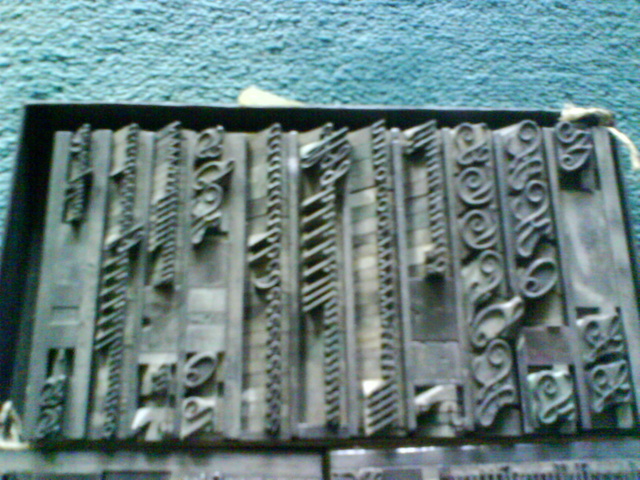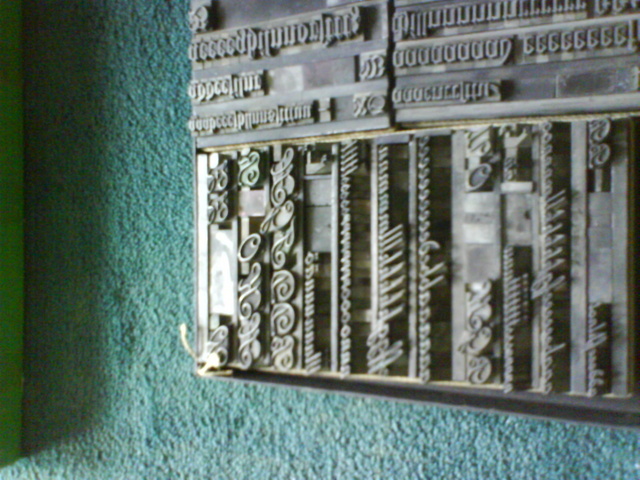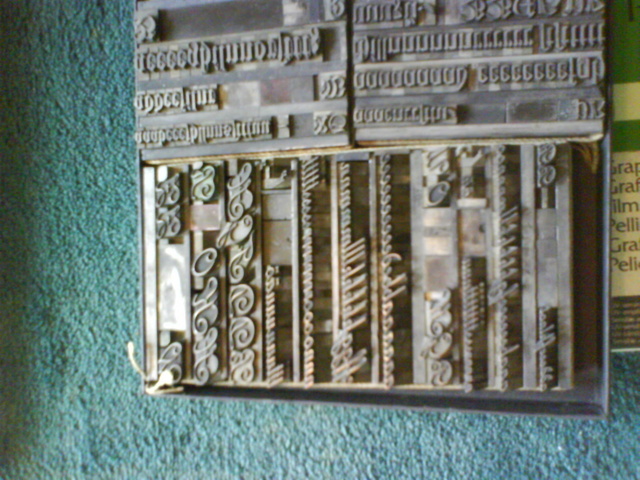
Ich habe bisher alle meine Schriftbücher durchsucht, habe allerdings keinen Treffer erzielt.
Nun hoffe ich hier auf Erfolg. Ich habe mal ein (schlechtes) Bildchen beigefügt.
Etwas zur Vorgeschichte. Ich habe einige Schriftfragmente "gerettet". Alles andere ging oder geht (demnächst) in die Schmelze. Es gibt zu dieser Schrift leider auch keine Schriftmusterbücher mehr. Was mich allerdings wundert, weil ich alle Schriftmusterbücher der betreffenden Firmen habe.
Anbei zwei weitere schlechte Bilder. Achja, die Kirnberg ist es nicht. Entstehungszeit etwa Jahrhundertwende...
Wenn mich meine schwachen Augen nicht sehr täuschen,
handelt es sich bei der Schreibschrift um die Batarde der
Bauerschen Gießerei (um 1915).
Sicher kann ich das aber erst mit einem besseren Foto beantworten.
Nee, die sind mir nicht so wichtig. Es ging mir lediglich um die Batarde, weil ich die nirgends in den Schriftmusterbüchern der betreffenden Firmen entdeckt hatte. Nochmals Dank.